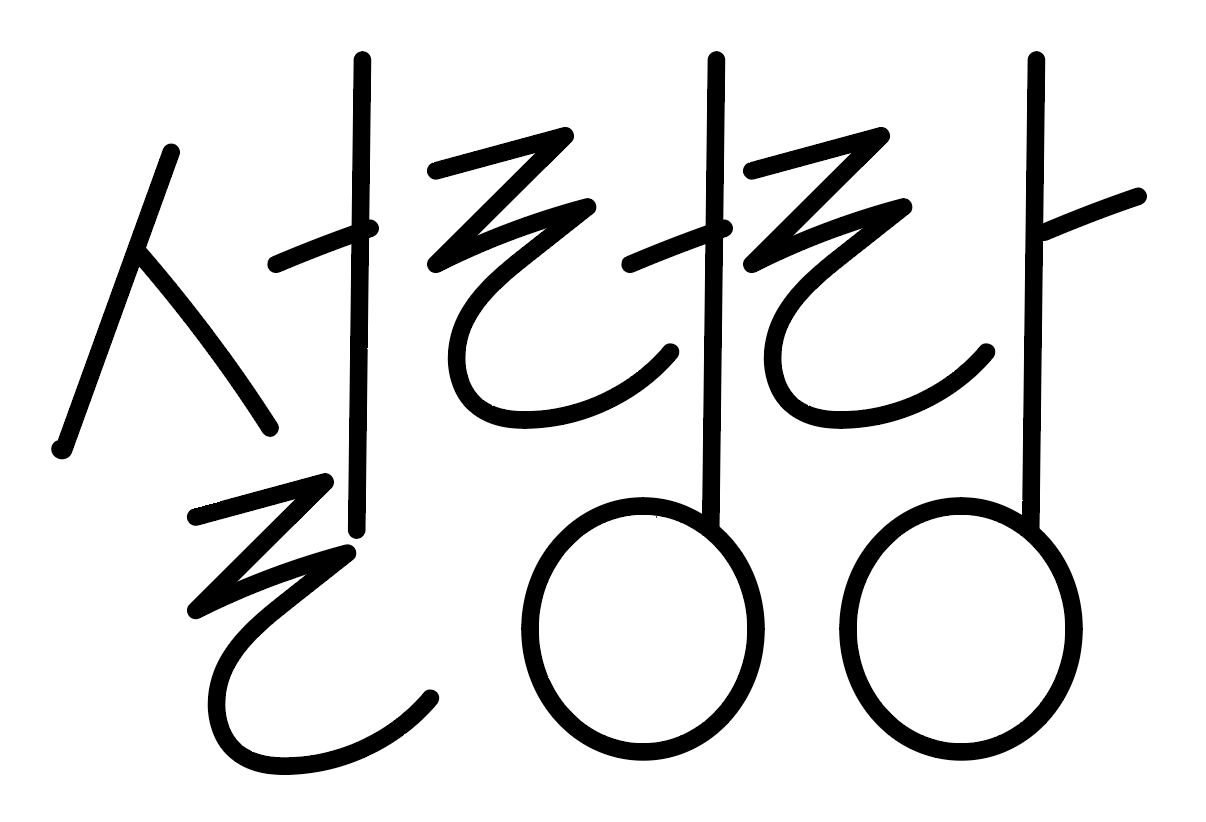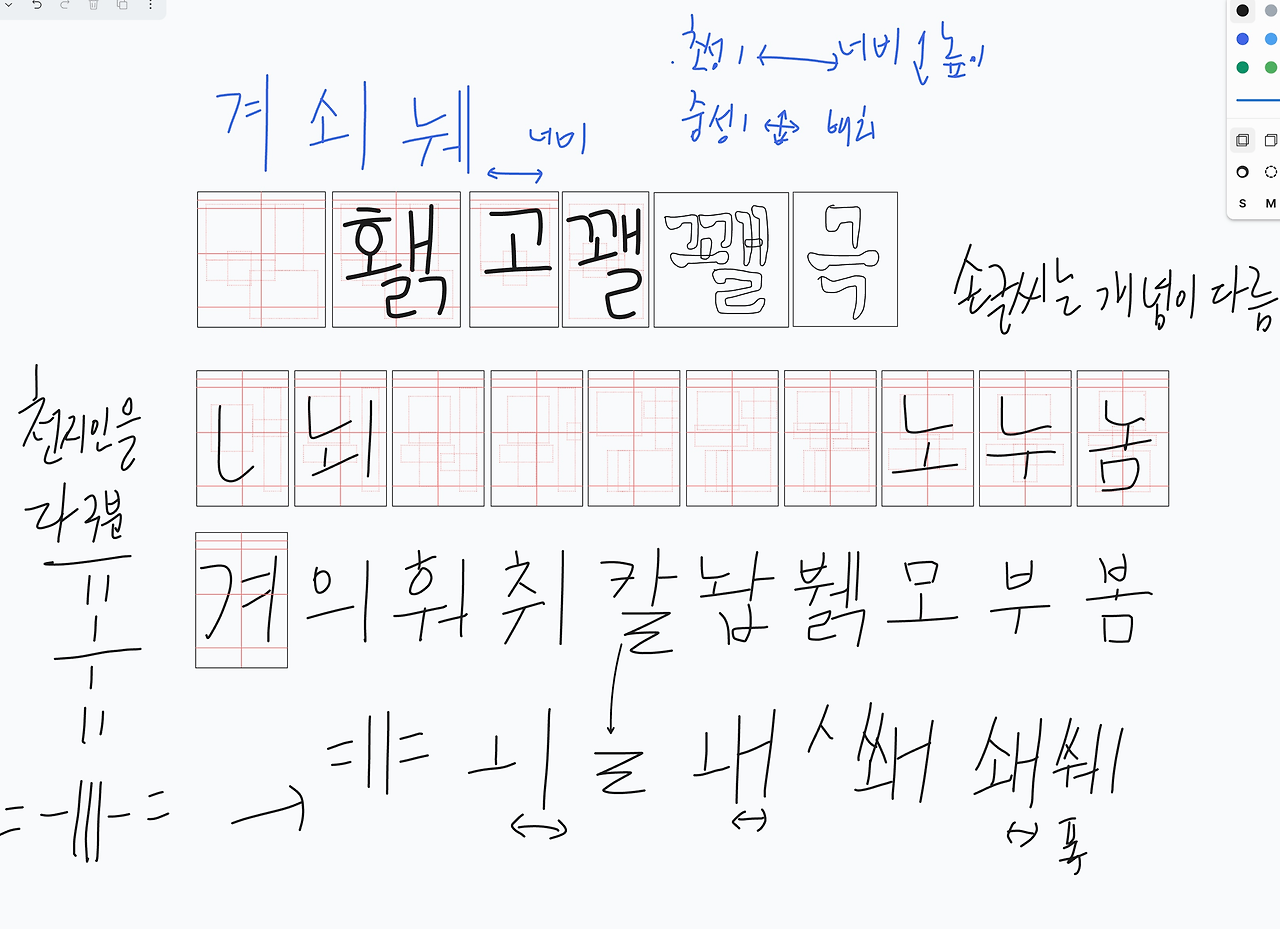
온라인에서 손글씨 폰트를 만들어주는 서비스를 준비 중
타이포용 디자인 폰트가 쉽다고 한 게 가이드로 일관성 있게 배열하면 됩니다
그런데 손글씨는 그렇게 배열이 안됩니다. 지금 프로그램 개발은 일단 끝났는데 구성을 아예 다른 방식으로 바꾸고 있습니다. 원래 제가 하려는 게 로봇이 반성문 쓰는 폰트를 만드는데서 시작했어요
스트로크 기반의 폰트를 만들고 있으며 향후 손글씨 폰트도 필기체나 캘리그래프처럼 플로팅머신, 스티치머신, 레이저커팅기처럼 기계가 인지하기 쉽고 압력감지가 가능한 형태로 만들려고 하고 있었습니다.
기존 폰트와 달리 너비에 민감해지는 형태가 되어 간격을 동일하게 하면 사람이 쓴 거 같지 않은 기계적인 폰트가 되게 됩니다. 사람의 손글씨인데 그렇게 하면 안 될 거 같아서 방향을 아예 바꿔 생각하기로 했습니다.
일단 한글 천지인처럼 다 구분해서 배열하는 형태를 생각했고 그 각각의 간격을 다른 글자의 모양에서 각도가 달라진 형태를 이용하기로 했어요. 사람은 직선을 매번 같이 그릴 수 없습니다. 조금씩 다릅니다.
그리고 몇 번 반복된 것을 약간씩 다른 레이아웃으로 맞춰야 사람 같은 글씨가 됩니다. 그래서 폰트를 5벌~10벌 배열 단위로 만들어서 랜덤 하게 섞어서야 절대 같은 글을 못쓰는 사람의 느낌을 줄 수 있습니다.
기계적으로 가능한 것이라서 특허가 될지는 모르겠지만 사이트에서 손글씨 쓰면 한 번에 폰트가 10벌 나오게 되고 그리고 사람이 똑바로 글을 쓸 수 있다는 생각은 안 하고 일정 두께도 못 그리니까 웹 드로잉 기반의 tldraw를 사용하기로 했습니다.
가이드를 자동 생성해서 그 파일 위에 글자를 쓰면 됩니다. (종이로도 템플릿 위에 쓰고 촬영해서 보내면 가능)
200자 정도의 글자와 10여 개의 문장을 따랐으면 사람에 가깝고 템플릿을 선택한 대로 폰트가 한 번에 나옵니다.
출판사를 하니까 엄마의 손글씨 노트를 제작해서 온전한 글씨에 대한 부분을 진행할 예정입니다.
일정한 폰트 스타일을 넣었을 때 나오는 폰트와 달리 매번 다른 글자를 쓰는 사람은 이응 하나도 수많은 모양이 생기게 됩니다.